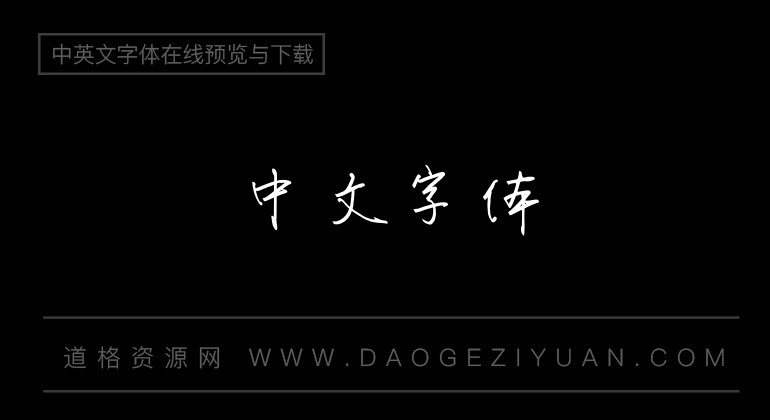
小箱子手写字体
小箱子手写字体是一款经典的汉字手写字体,它的特点是字形简洁、笔画流畅、结构清晰,是目前最受欢迎的汉字手写字体之一。小箱子手写字体的笔画比较细腻,可以表现出汉字的细节,使文字更加清晰、立体,适合用于文字排版、手写等场景。
小箱子手写字体是一款非常不错的手写艺术字体,具有很好的视觉感,适合于文化类的宣传设计、商业类品牌的广告和产品包装设计以及个性化文字排版等较多场景。